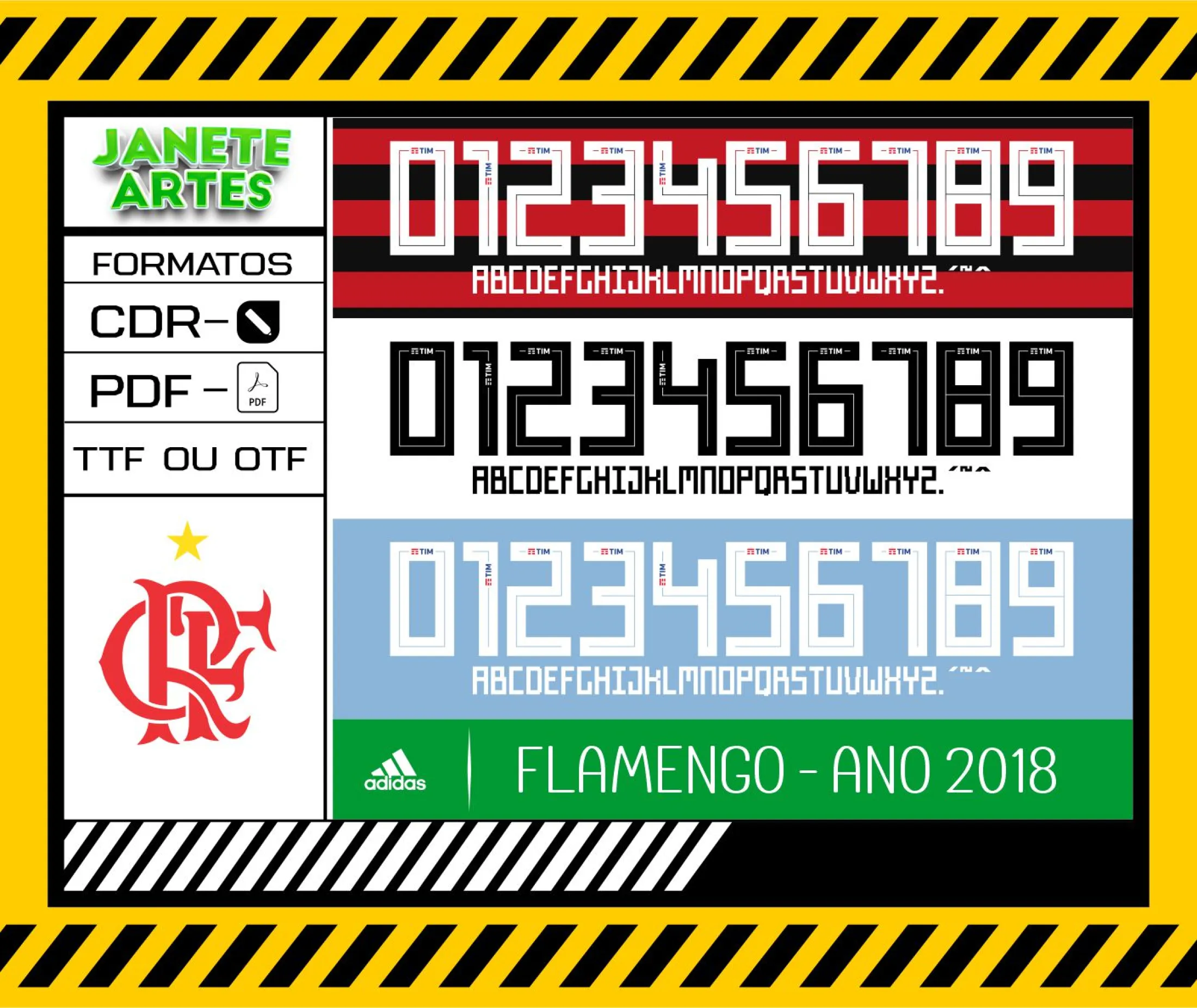
Fonte de Time Tipografia Flamengo 2018
Tenha em mãos a Fonte de Time Tipografia Flamengo 2018 e personalize suas camisetas com a identidade do Mengão! Arquivo digital perfeito para criar camisas exclusivas e arrasar em qualquer ocasião.
Uma paixão em forma de fonte
Imagine aquela tarde de sábado, você reunido com os amigos para assistir ao Flamengo jogar. Todos com suas camisas personalizadas, cada detalhe pensado para mostrar amor pelo time. Foi assim que nasceu a ideia da Arte Fonte Time Tipografia Flamengo 2018 para Camisetas: um arquivo que traduz a energia e estilo do Mengão em cada letra. De começo simples a protagonista nas arquibancadas, essa tipografia representa a paixão pelo futebol carioca em sua melhor forma.
• Permite editar números, nomes e palavras com a tipografia original
• Combine a Arte Fonte Time Tipografia Flamengo 2018 para Camisetas com logos e elementos adicionais do Flamengo para um visual mais autêntico.
Seja para criar sua camisa da torcida ou um presente especial, a Arte Fonte Time Tipografia Flamengo 2018 para Camisetas é a escolha certa para mostrar seu amor pelo Flamengo com estilo e autenticidade. Aproveite e coloque seu projeto em campo! ⚽🔥